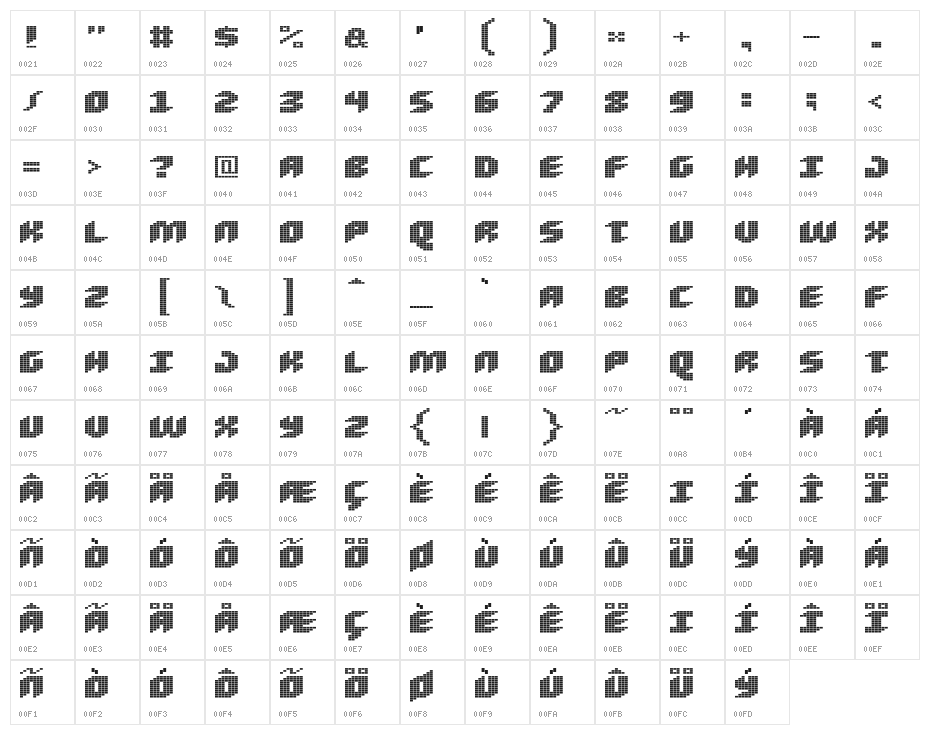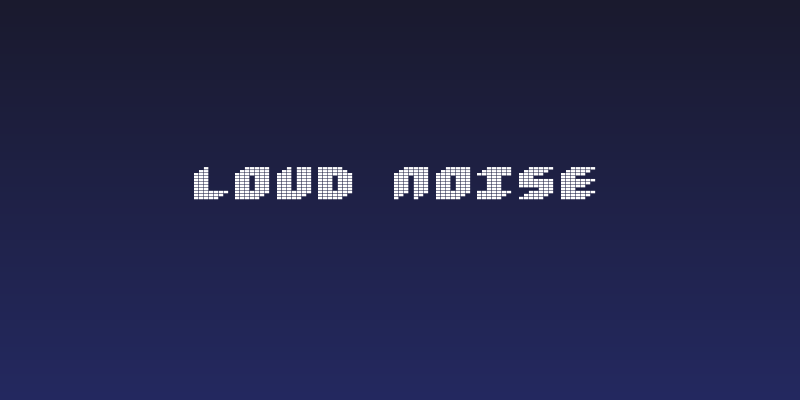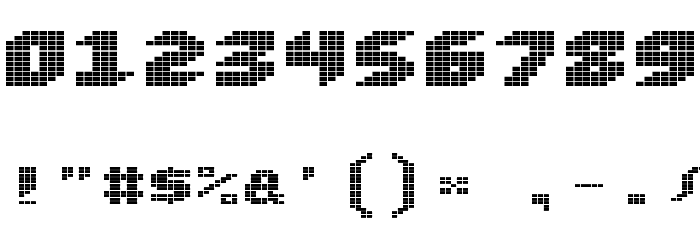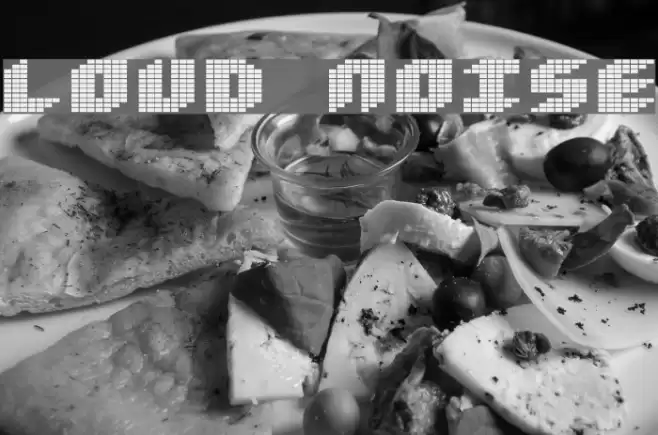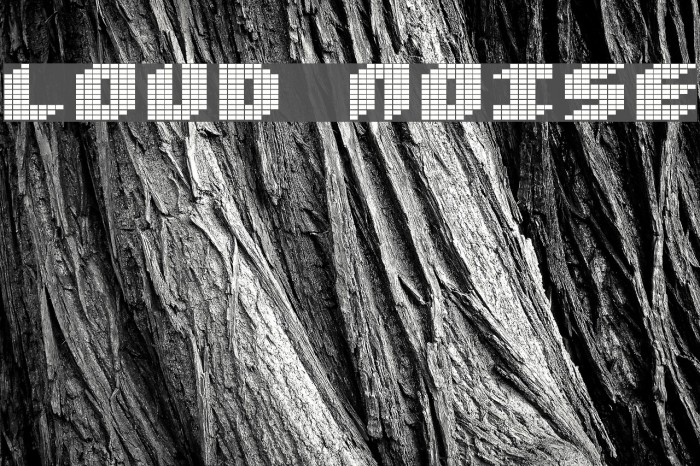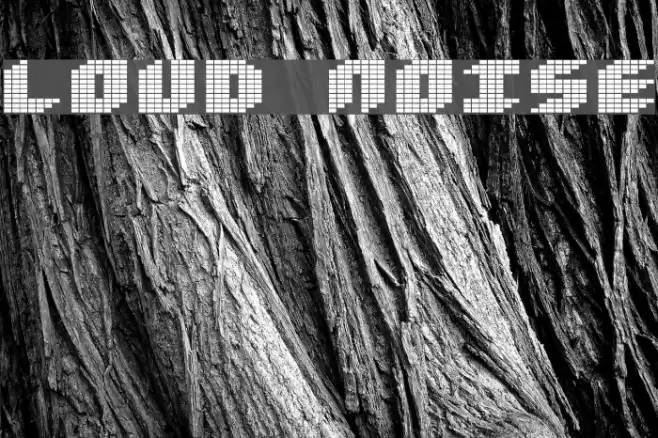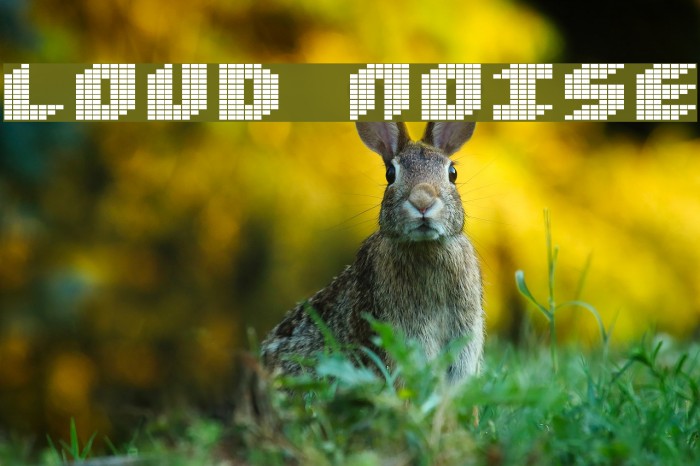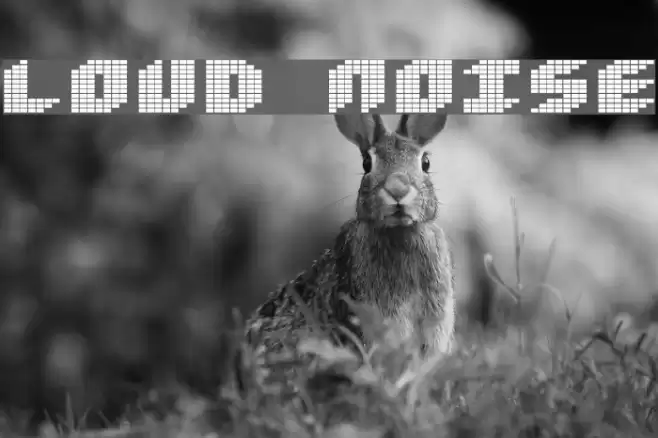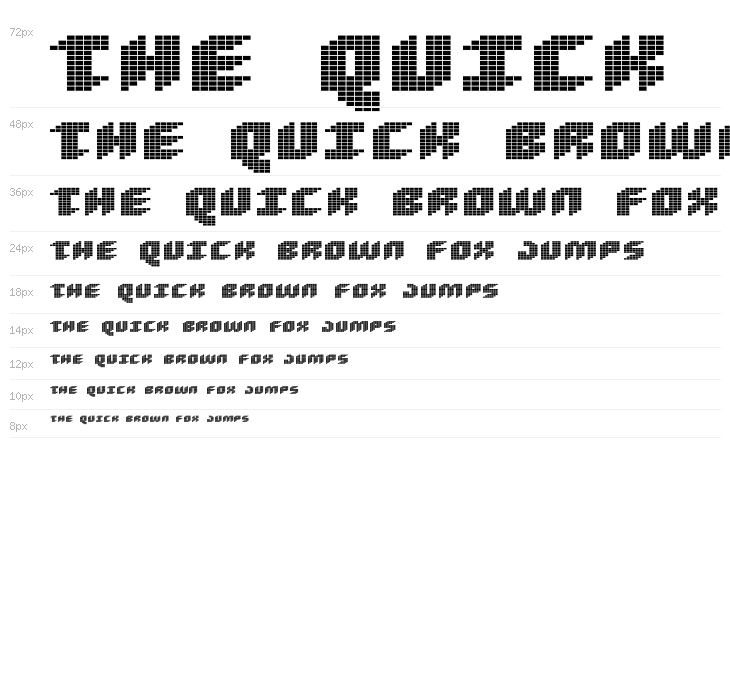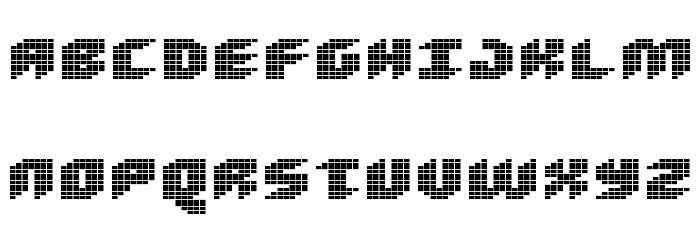
Loud noise Font
| カテゴリ | Pixel |
| 全体的なスタイル | Modern, Digital, Retro |
| 用途 | Headlines, Logos, Digital Displays |
| おすすめプロジェクト | Ideal for video game design, tech-themed posters, digital art projects, and any creative work that requires a futuristic or retro digital appearance. |